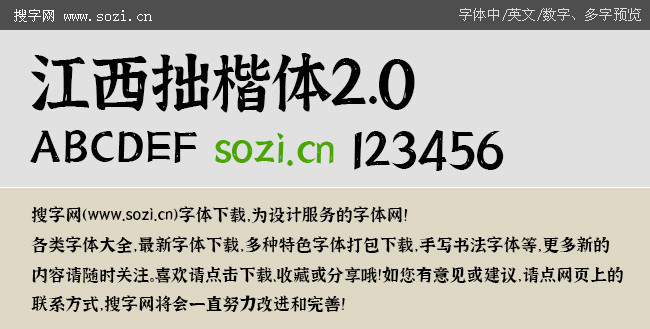
江西拙楷體2.0
搜字網(wǎng)給大家提供一款江西拙楷體2.0中文字體下載,這是一款由設(shè)計師黃煜臣設(shè)計的,以作者家鄉(xiāng)江西命名的手寫風(fēng)格的書法字體,字體低調(diào)內(nèi)斂,樸實無華毫不張揚!而且免費提供給大家使用!適合海報設(shè)計、包裝畫冊等宣傳廣告等應(yīng)用。